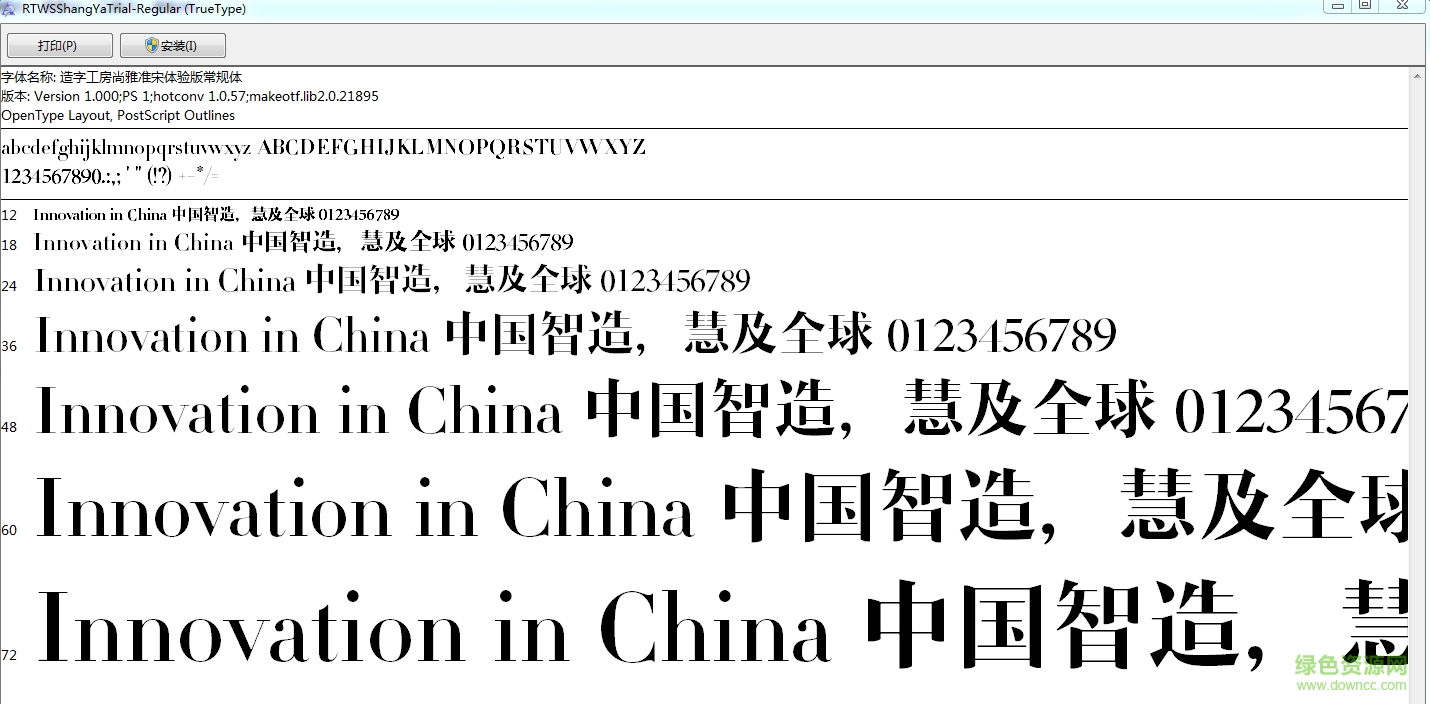
造字工房尚雅準宋是一款造字工房類優(yōu)雅清新風(fēng)格字體軟件,尚雅準宋體帶著宋體柔和的影子,與尚雅比較文雅的風(fēng)格融合一起,整體給人非常舒適的感覺,也深受廣大書法家的喜愛,還有更多好看字體盡情期待,歡迎到綠色資源網(wǎng)下載體驗!
造字工房尚雅準宋比傳統(tǒng)的宋體比方較為柔和,筆畫設(shè)計簡潔,用途廣泛。